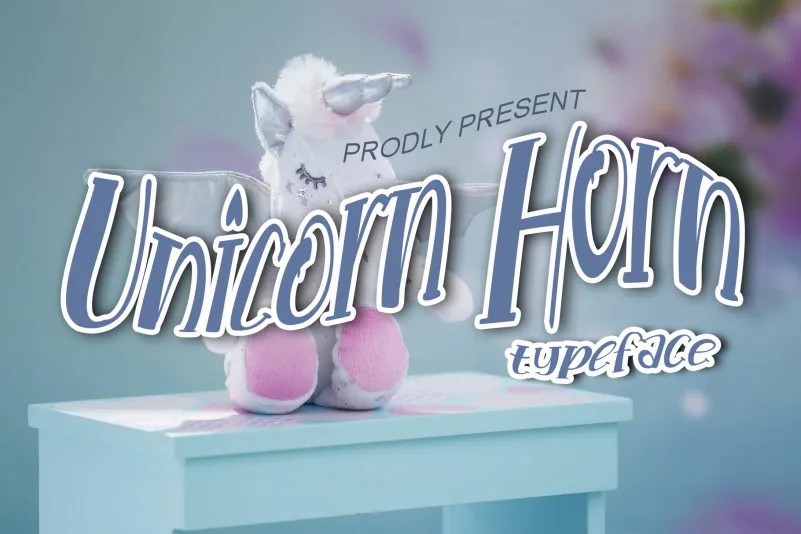
Unicorn Horn Font – Fonte Grátis
Unicorn Horn Font
Esta é uma fonte de exibição simpática e encantadora, perfeita para aplicação em designs relacionados a animações infantis ou jogos infantis. Seja que você esteja criando um jogo infantil, estilizando anúncios, design de logotipos ou qualquer outro projeto que precise de uma pitada delicadamente amorosa, esta fonte será uma escolha incrível. Ideal para aqueles projetos em que você busca algo agradável e encantador, seja ele um slogan, um título ou simplesmente adicionar um toque único ao seu design. A Unicorn Horn Font é o elemento perfeito para tornar seus projetos ainda mais memoráveis e divertidos.